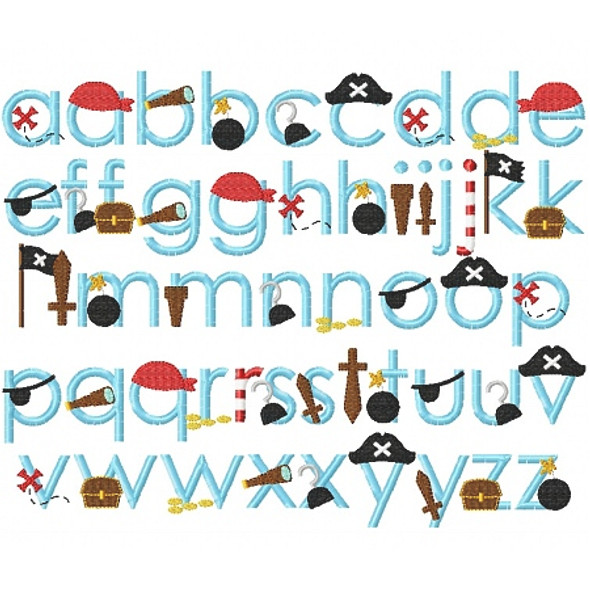
Шрифт — Caribbean / Creativo.one
Красивый шрифт, который прекрасно подходит для работы в фотошоп. Без поддержки русского языка.
30 лучших пиратских шрифтов (бесплатных и премиальных) для дизайнеров
Правильный шрифт может поднять проект графического дизайна на новый уровень. Ничто так не создает приключенческую тему, как широкий выбор пиратских шрифтов.